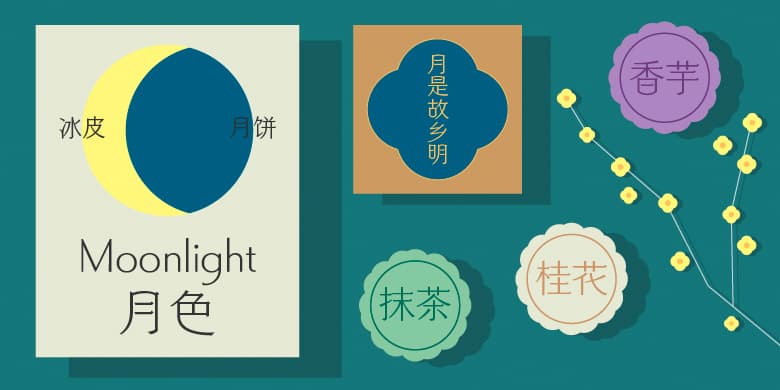
方正FW珍珠体
2020年方正推出与日本合作的一款字体。这款创意字体造型高端、典雅,一扫普通日文字体特有的土气。其独特的造型和出色的品质,可以让打出来的单词直接用于标志也毫不逊色,而用于长文排版中则能展现出一种紧张感。横竖笔画具有细字重所特有的锐利感,并提高了字的重心,营造出现代时尚、高端雅致的氛围。字母数字兼具易认性和创意性,用于中日西文混排也能保证美观。
和文書体特有の泥臭さを排除した、上品で洗練されたフォルムのデザイン書体です。その独特のフォルムは、単語をそのままロゴとして使用できるほどのクオリティをもっており、さらには長い文章では緊張感を演出します。ウエイト「L」ならではのシャープな縦線と横線の組み合わせと、文字の重心を高めに取ることで、モダンでファッショナブルな上品さ、そしてシックな雰囲気を醸し出します。英数字は視認性とデザイン性を両立させ、和欧混合の文章でも、その美しさを損なうことのない書体です。